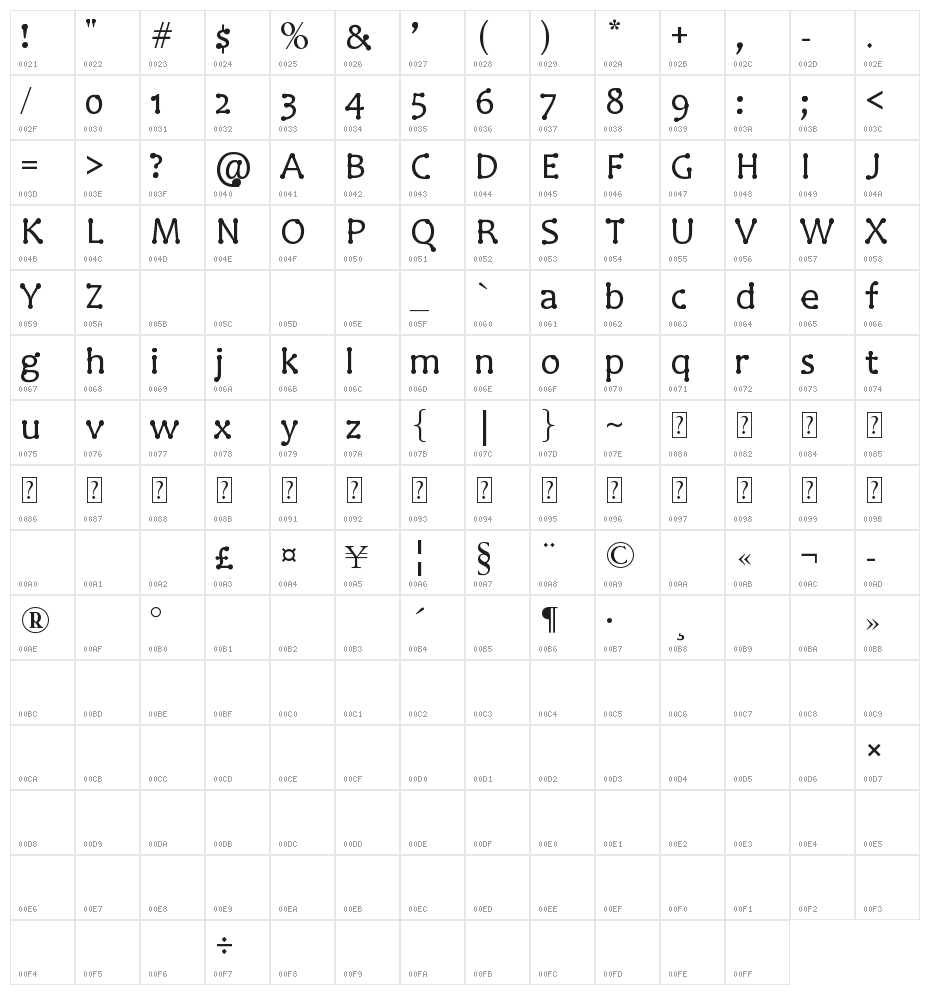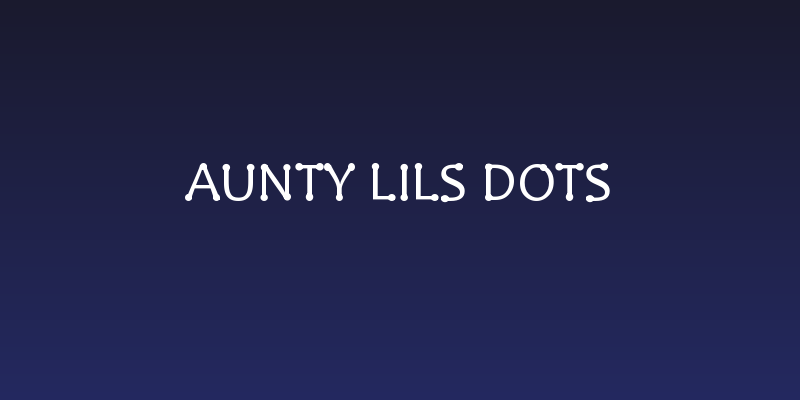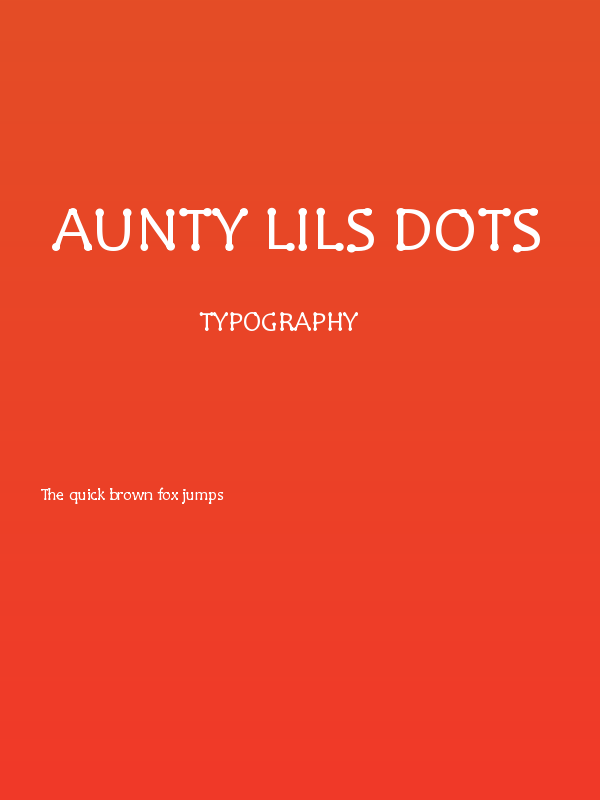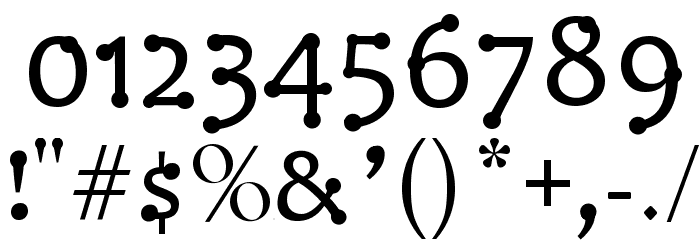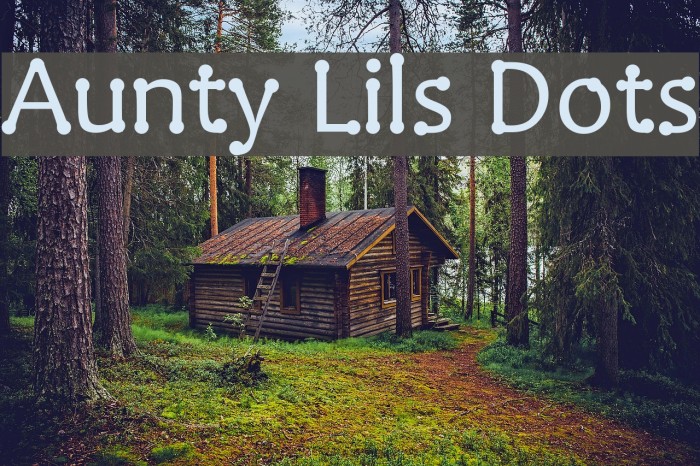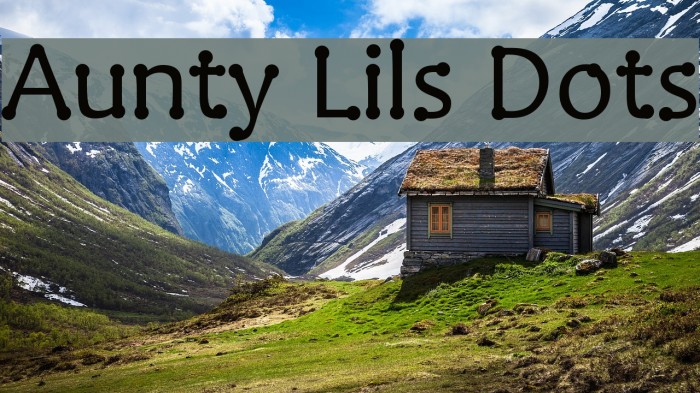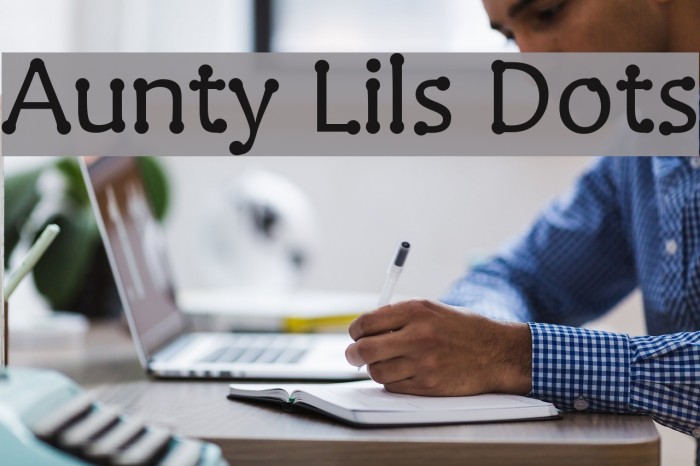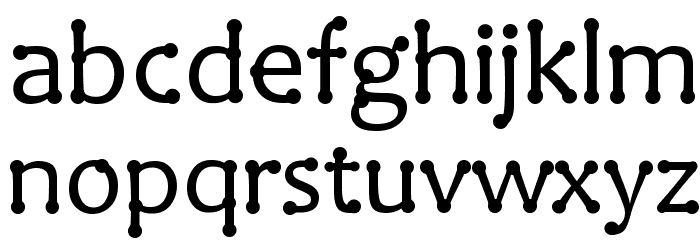
Aunty Lils Dots Font
| Estilo general | Playful |
| Caso de uso | Headlines, Logos, Creative projects |
| Proyectos propuestos | Ideal for children's books, playful branding, party invitations, and creative posters. |